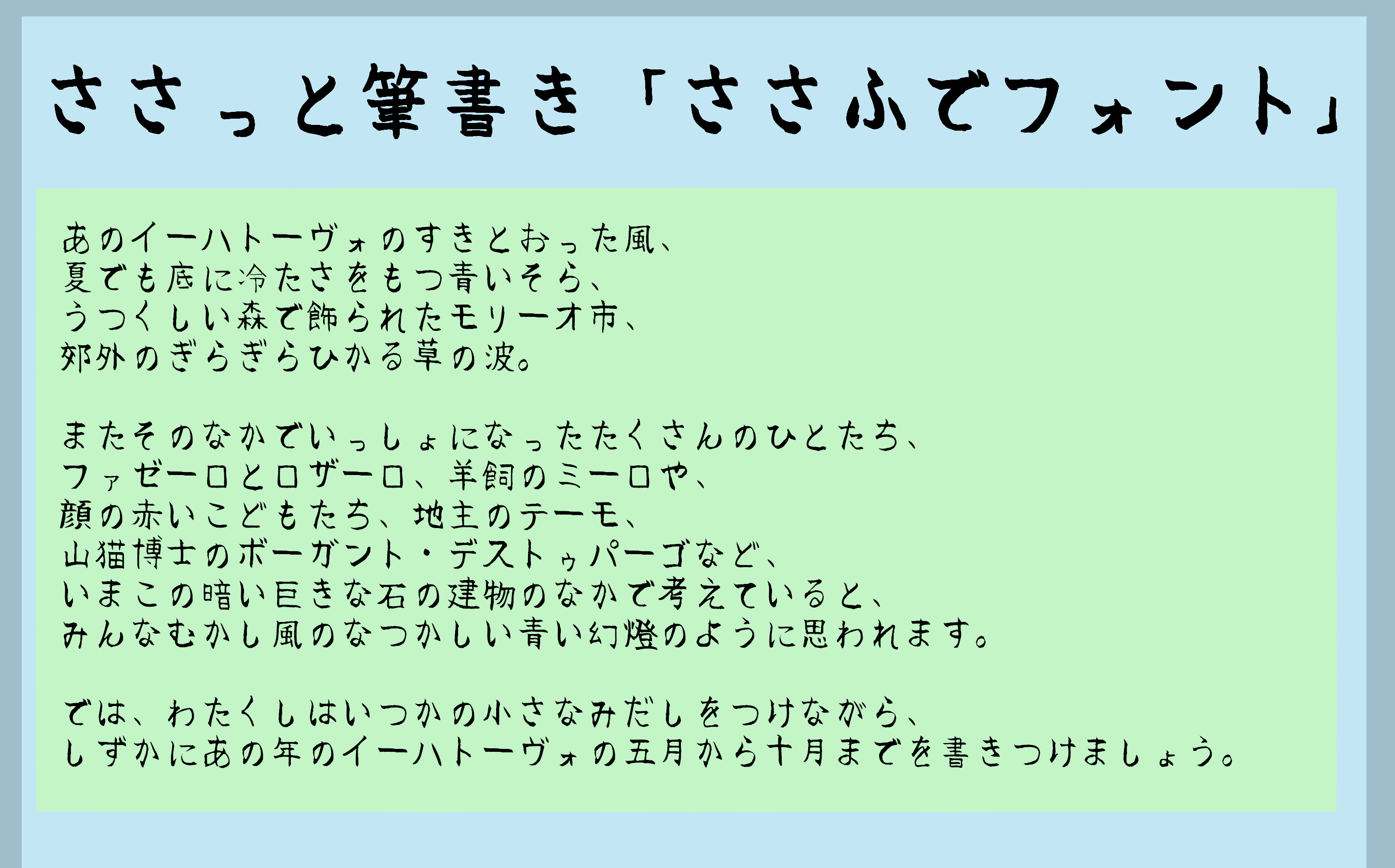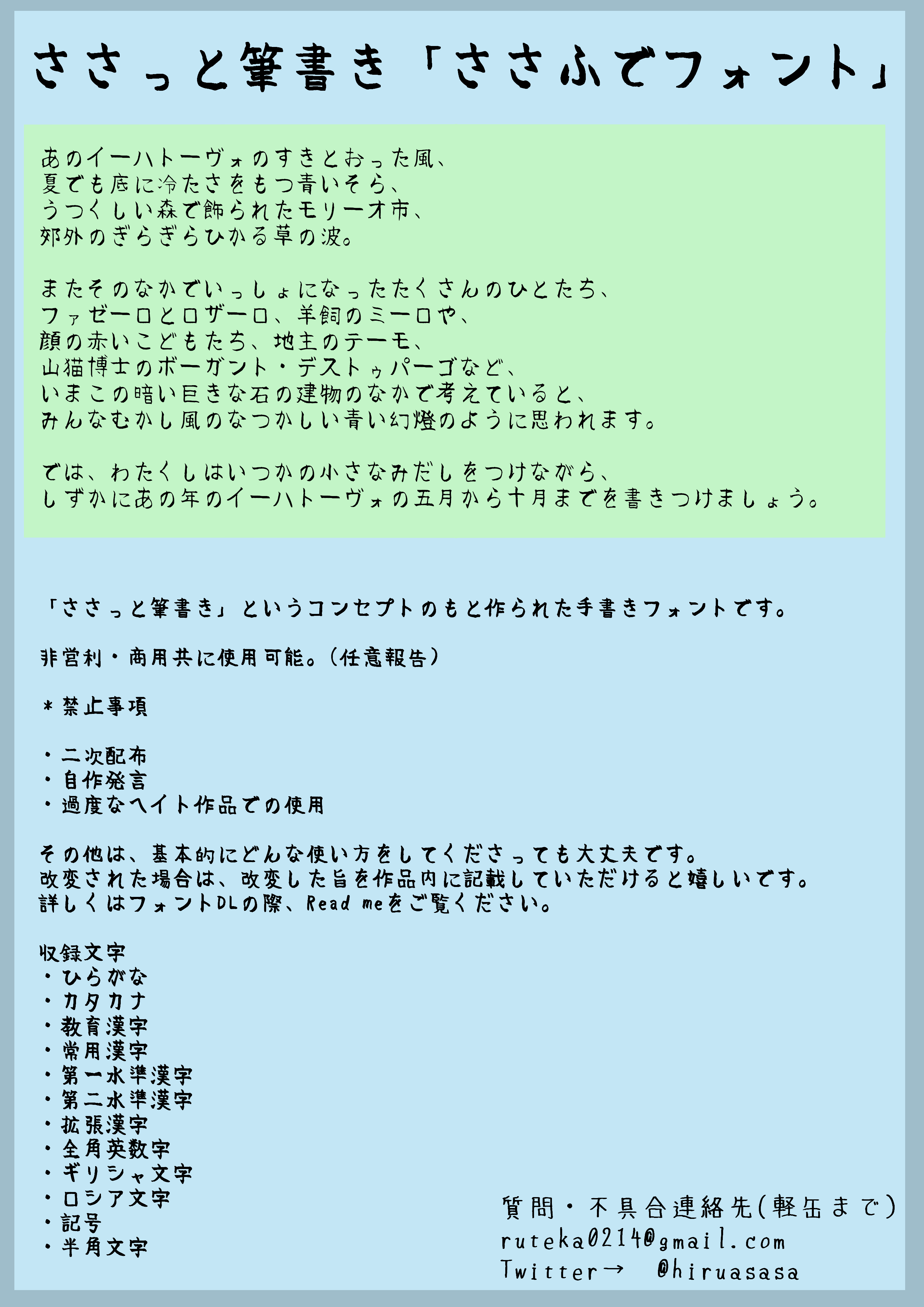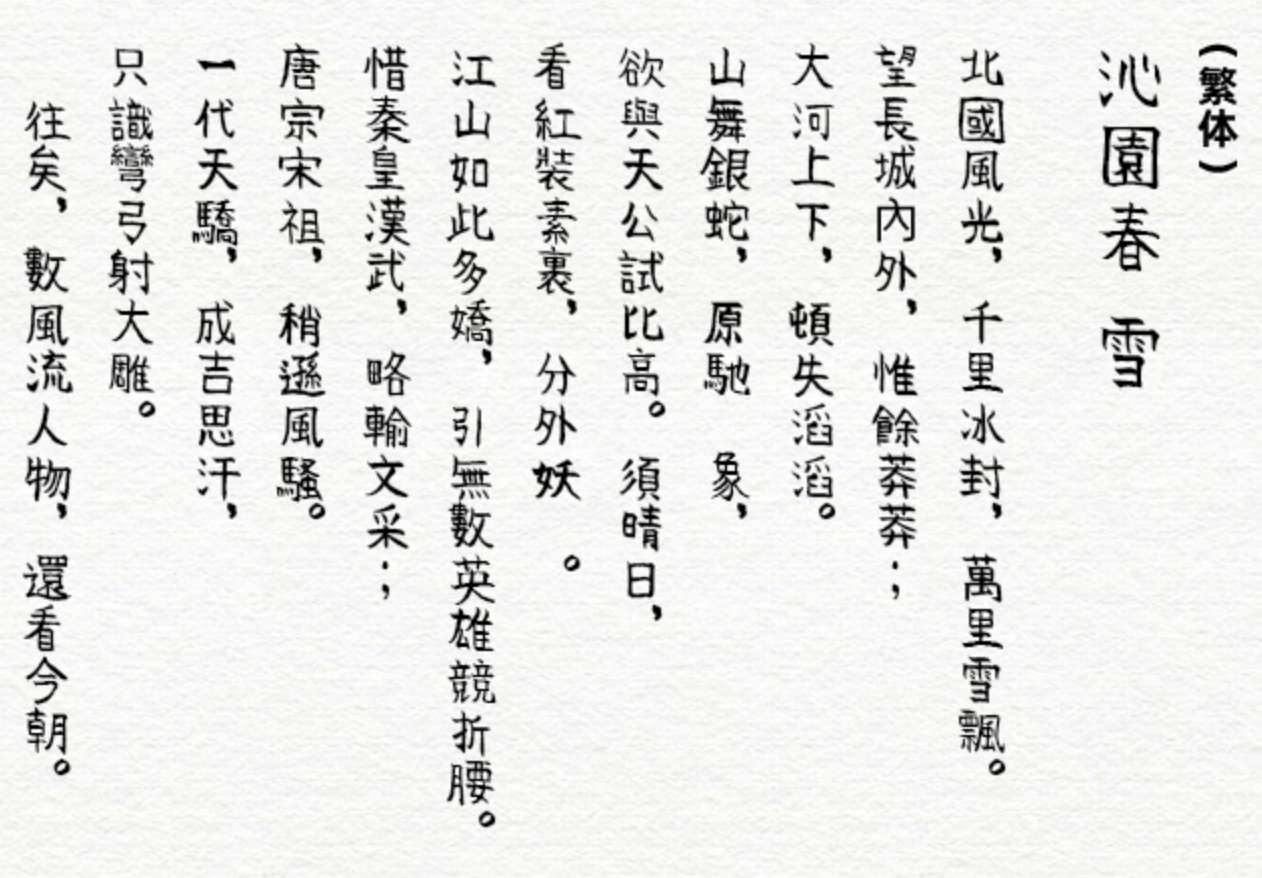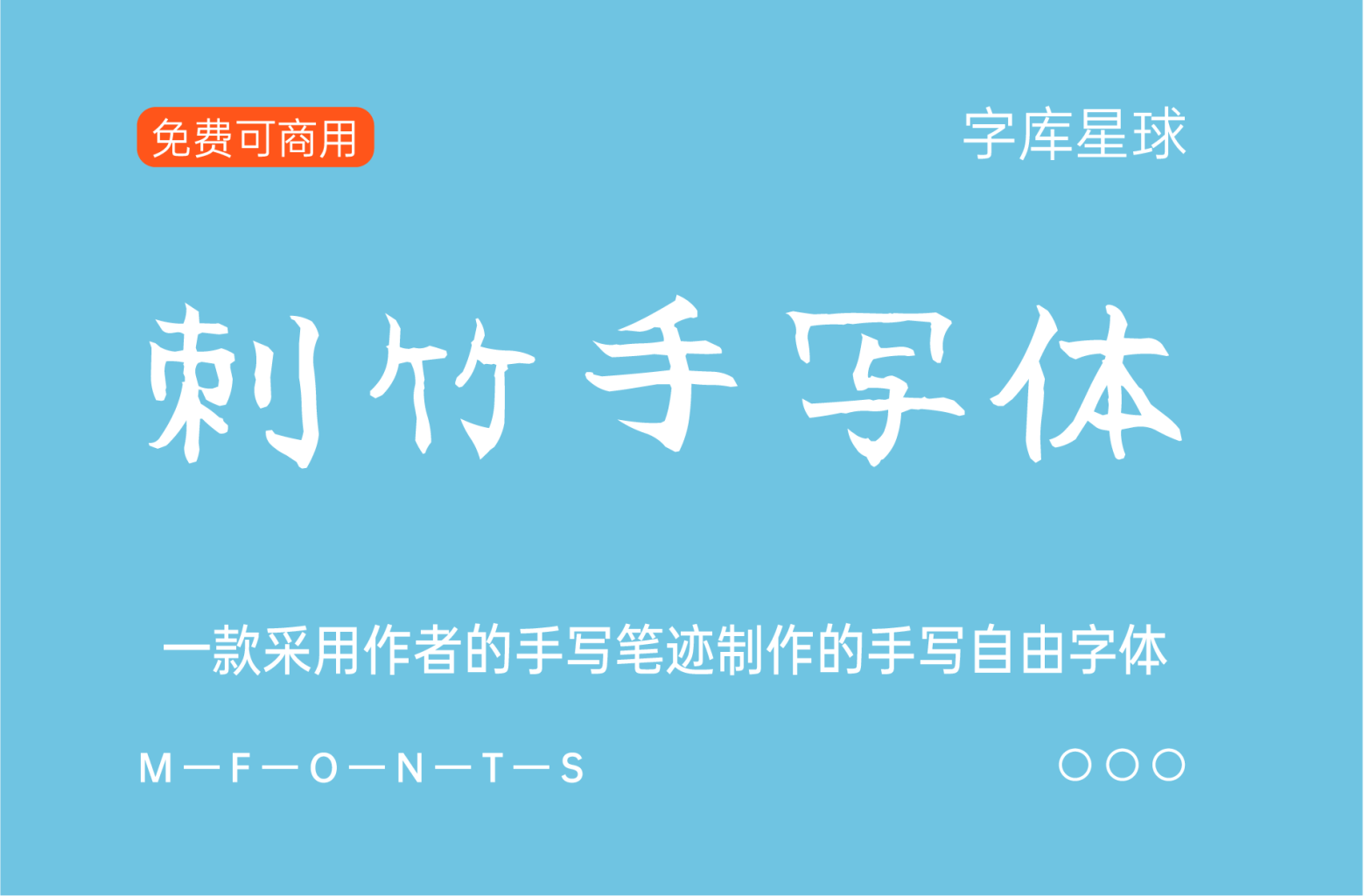
刺竹手写体
这是一种采用作者的手写笔迹制作的手写自由字体,采用TrueType格式。
[包含字符]
• 平假名
• 片假名
• 教育汉字
• 常用汉字
• 第一水准汉字
• 第二水准汉字
• 扩张汉字
• 全角英数字
• 希腊字母
• 俄文字母
• 记号
• 半角文字
刺竹手写体
这是一款免费的手写字体,直接体现作者的手写书法。